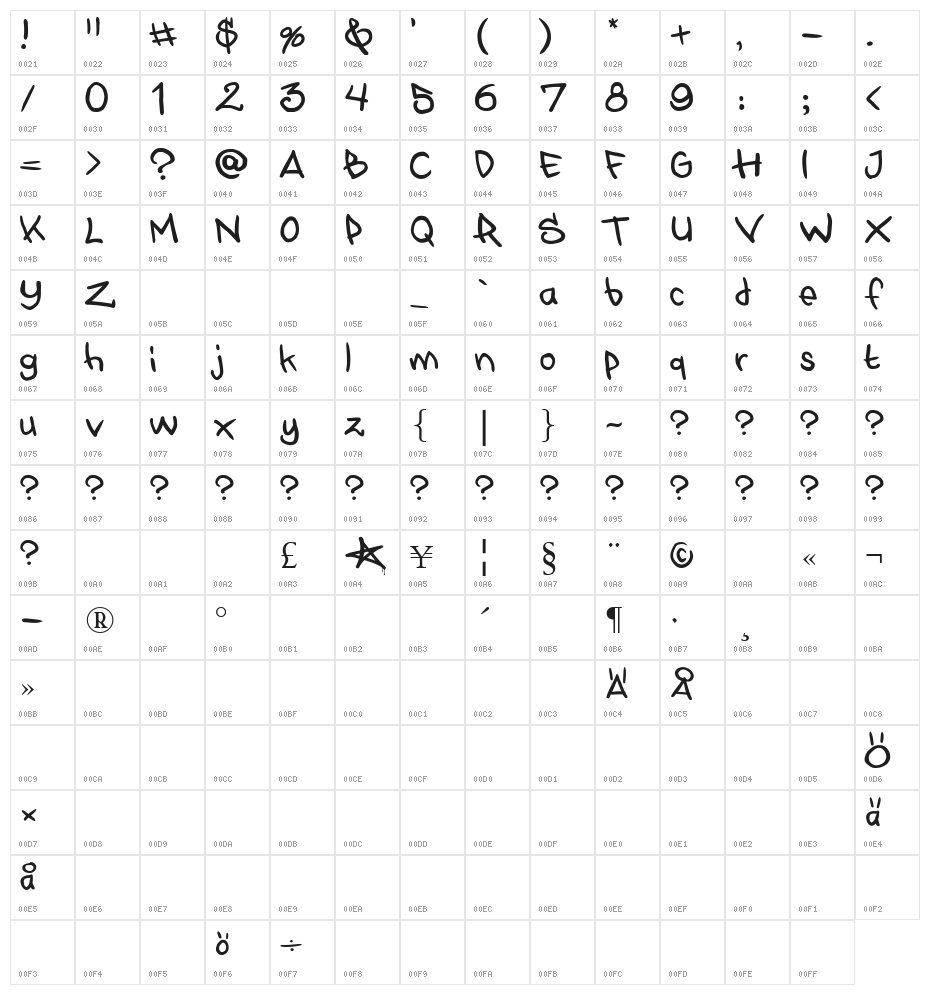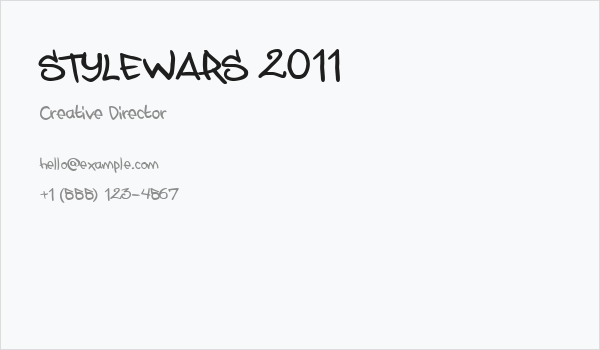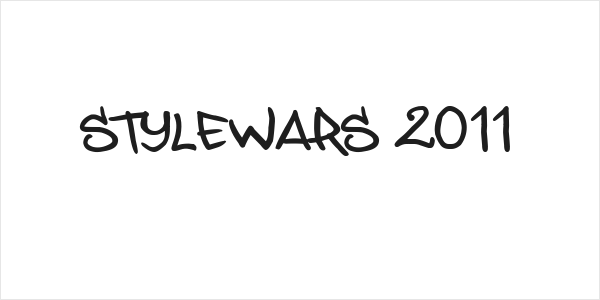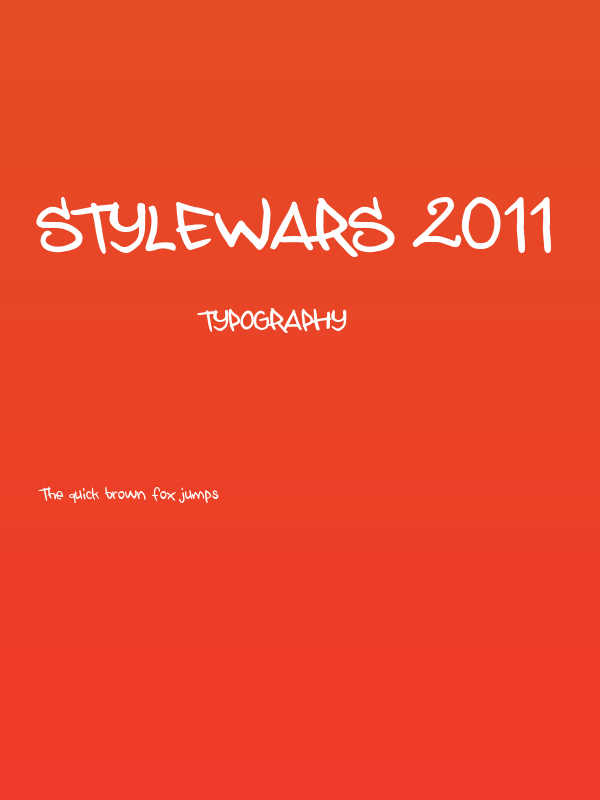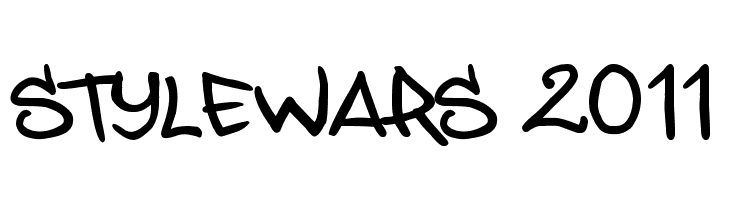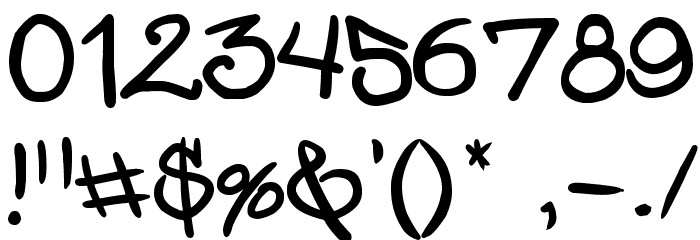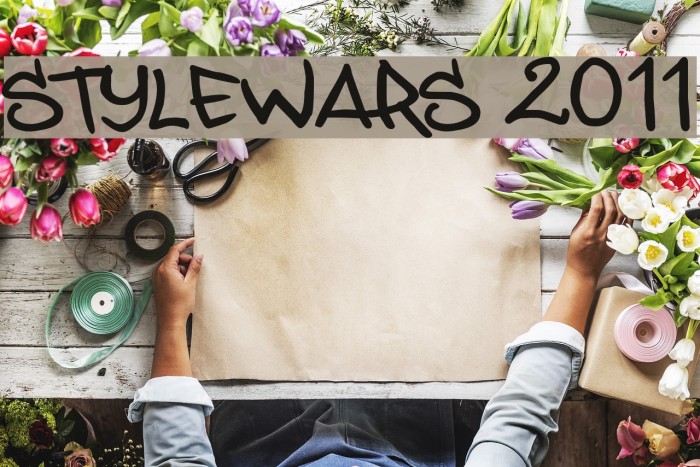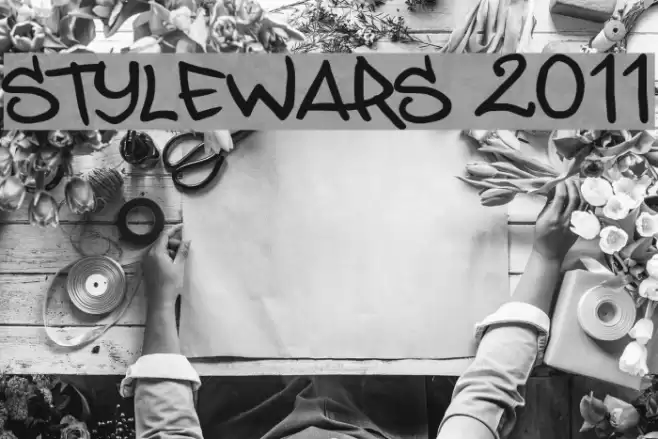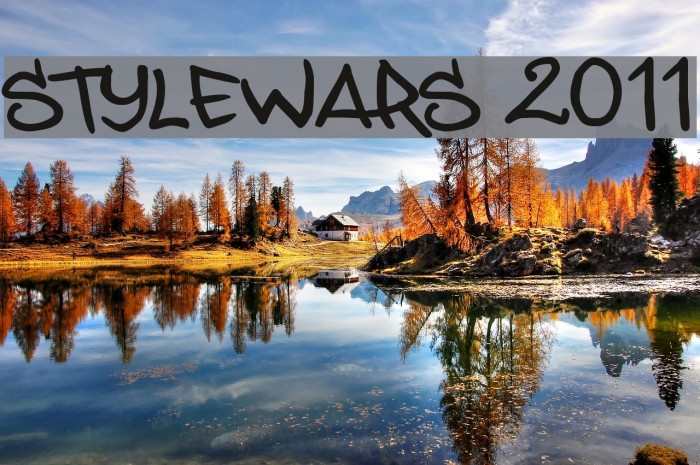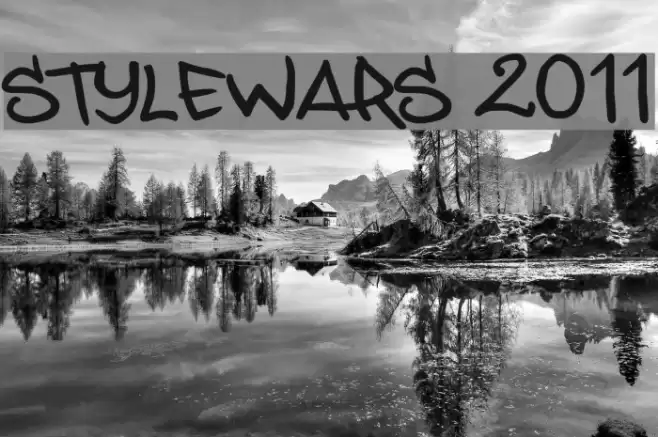
STYLEWARS 2011 Font
✎ Graffiti
| Общий стиль | Urban, Playful, Energetic |
| Рекомендуемые проекты | Ideal for street art designs, urban-themed posters, youth-oriented branding, and creative social media graphics. |